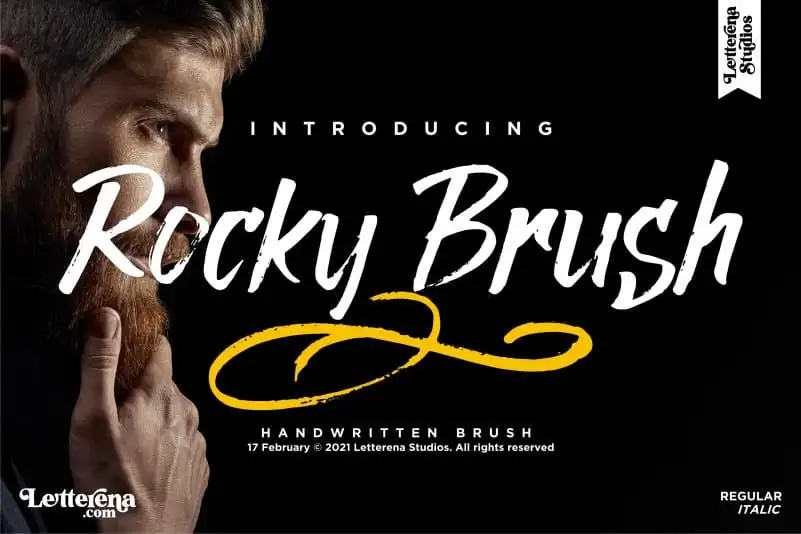
Rocky Brush Font – Download Grátis
A Rocky Brush Font é uma elegante opção para aqueles que desejam dar um toque sofisticado a seus projetos digitais. Com seu design suave e contínuo, essa fonte brush foi cuidadosamente criada para atender às necessidades de vários ambientes, desde embalagens de produto até cartões de festa. Este é um recurso exclusivo da designer letterenastudios, que oferece o ideal para designers de logotipos e projetos de marca, bem como para qualquer projeto que valorize a elegância e sofisticação do estilo brush. Seja para criar uma capa de livro, etiquetas para embalagens ou até mesmo um cartão de visita, a Rocky Brush Font traz a perfeição dos strokes brushy ao seu design, garantindo que seu trabalho seja imediatamente reconhecível por sua sofisticação única. Esta fonte é o complemento perfeito para qualquer projeto que necessite de uma aposta em estilo e sofisticação.